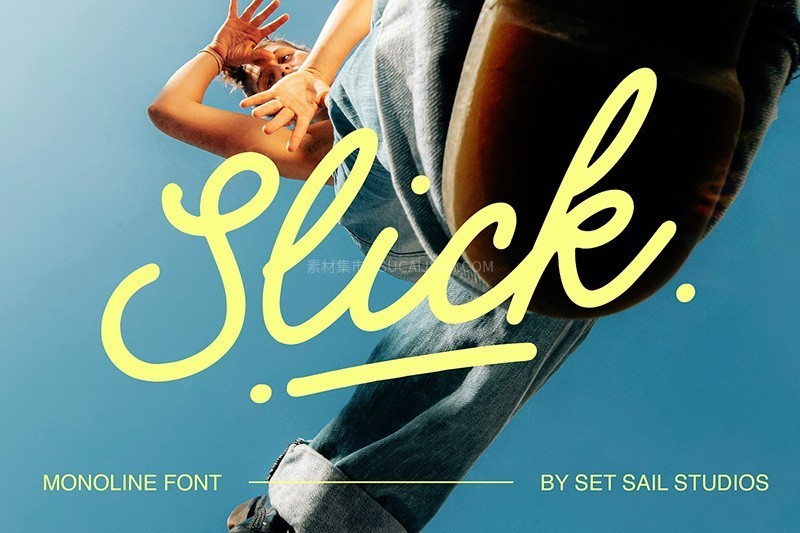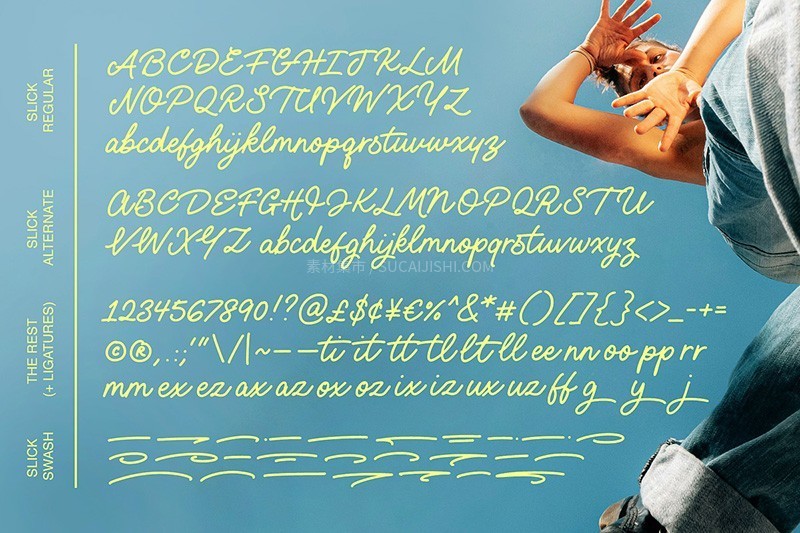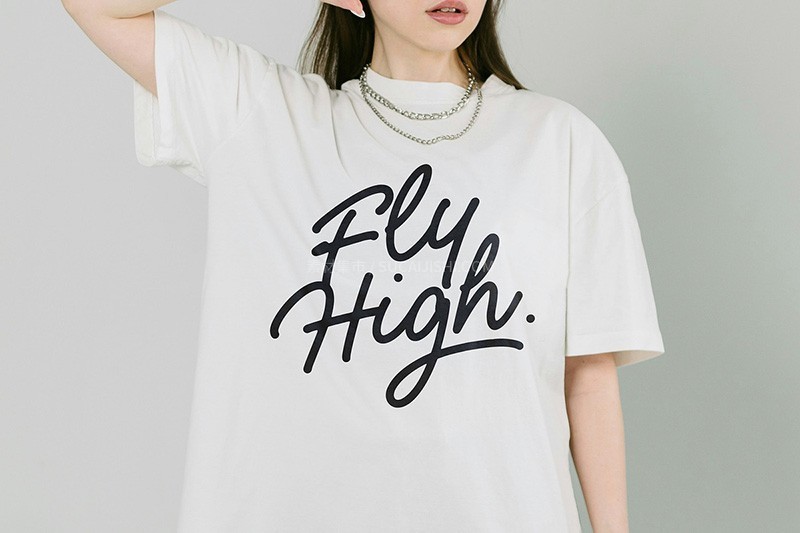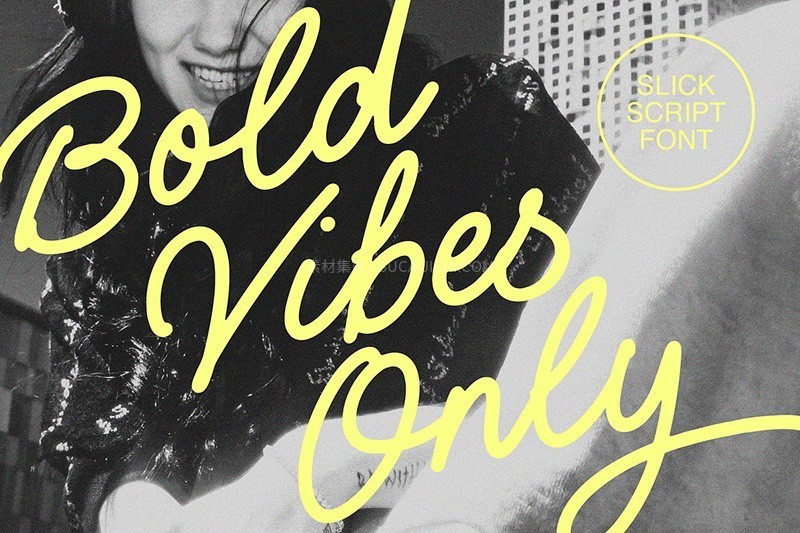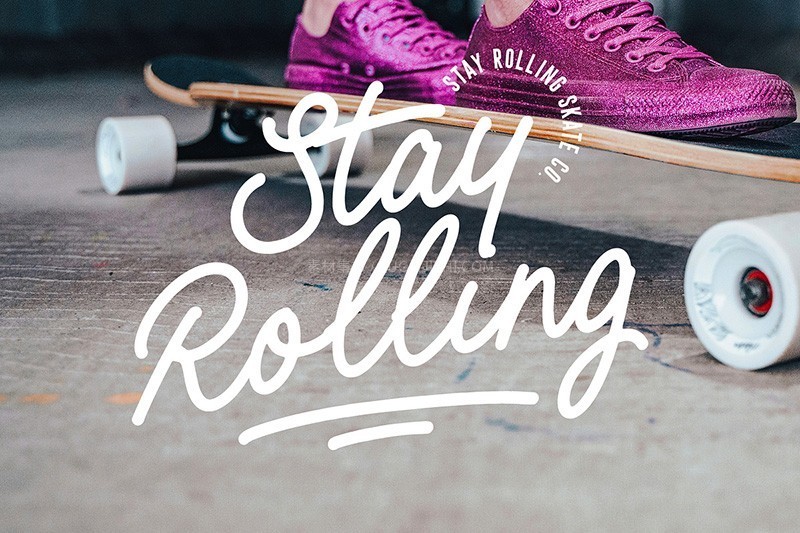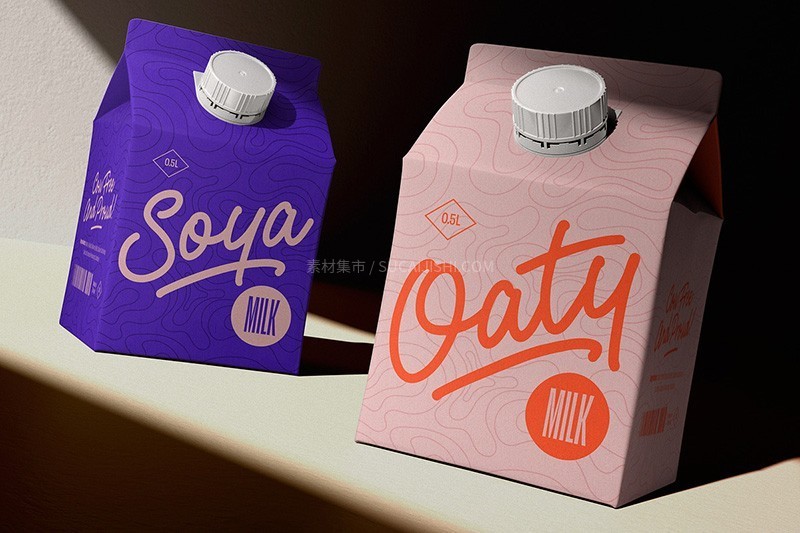
Slick流畅线条英文字体
Slick 是一款主打“酷炫、简洁、极度丝滑”的单线手写英文字体。它将清新活泼的草书笔触与现代简约美学完美结合。该字体功能极其丰富:除了标准的完整字符集,还包含一套完整的替换大小写字母包,方便你自由切换造型。最特别的是,它附带了 26 个精美花饰(Swashes),只需输入任意字母即可生成,专为添加优雅的下划线和装饰而设计,让你的文字排版更具节奏感。